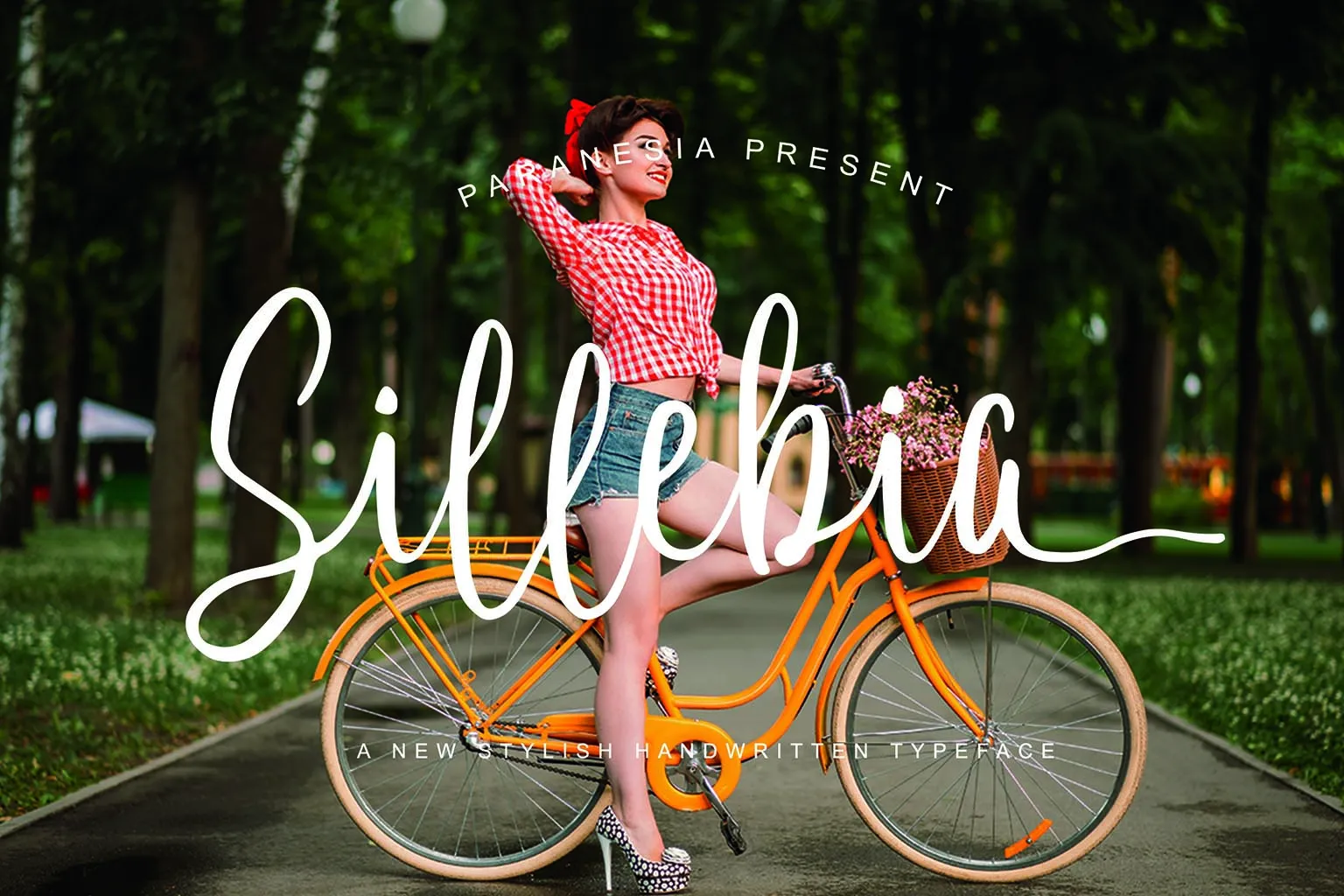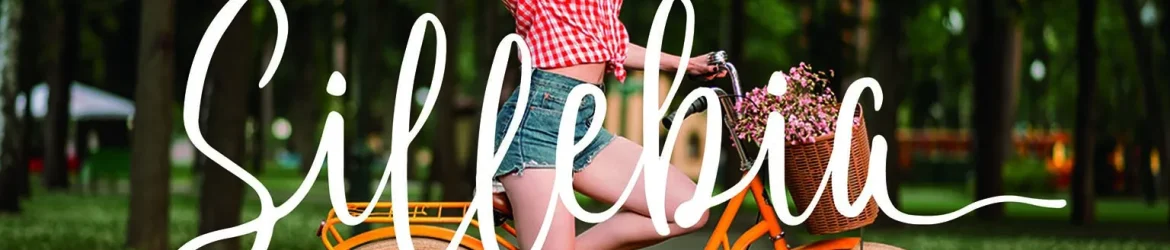
A fonte Sillebia Script é uma escrita manual que traz consigo a essência do papel de couro com traços delicados. Desenvolvida pelo designer Paranesia, ela oferece um toque autêntico e elegante, perfeita para gráficos envolventes e criativos. Sillebia Script é uma fonte que transmite confiança sem ostentação, ideal para criações de design em formato digital ou impresso que precisam se destacar com estilo. Com linhas suaves e detalhes cuidadosamente elaborados, ela é perfeita para textos de introdução, descrições de produtos ou qualquer tipo de conteúdo em seu site. A fonte não apenas torna o seu texto mais atraente, mas também reflete uma paixão pelo design que busca incorporar uma mão-dilatada na sua arte digital.